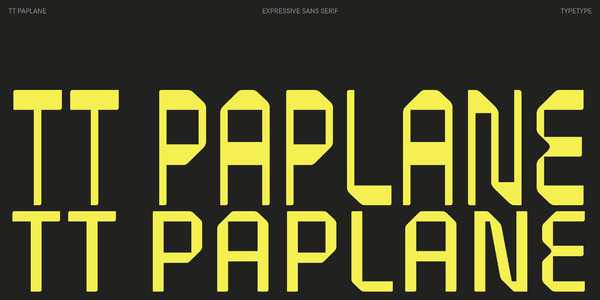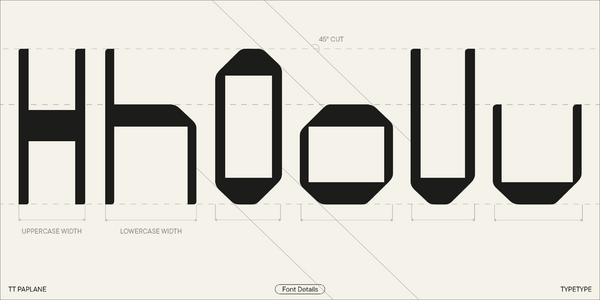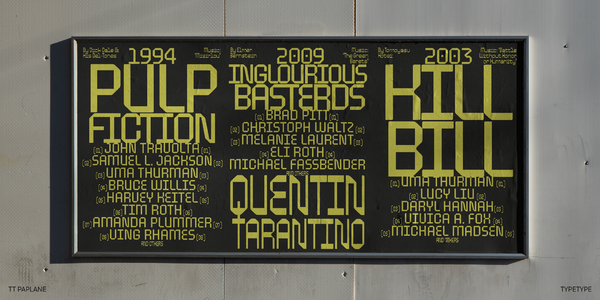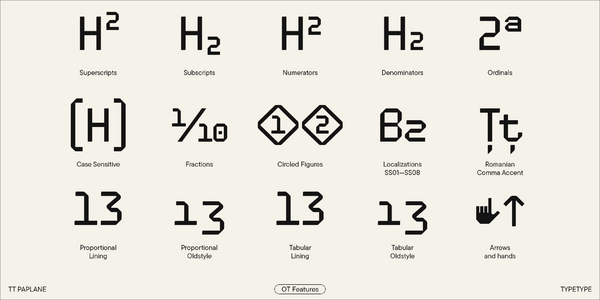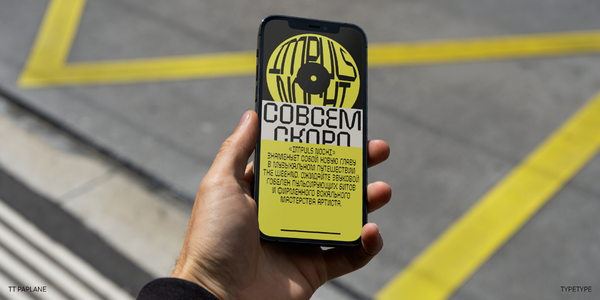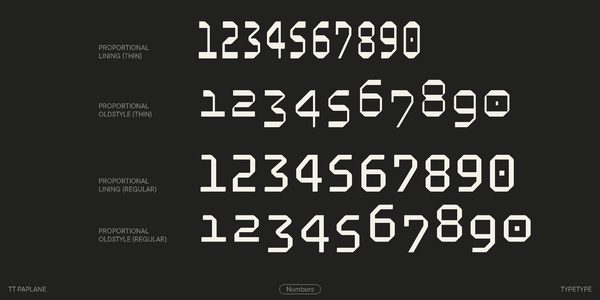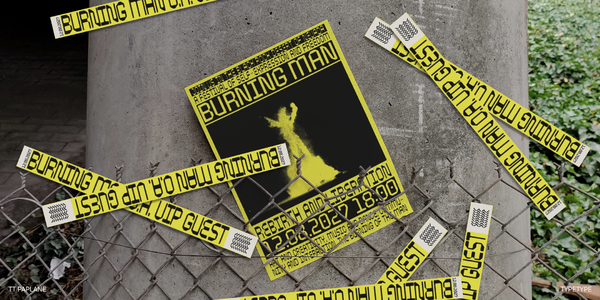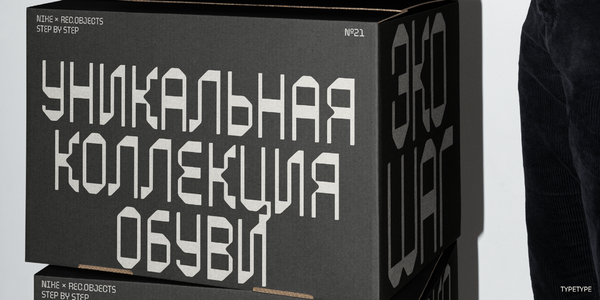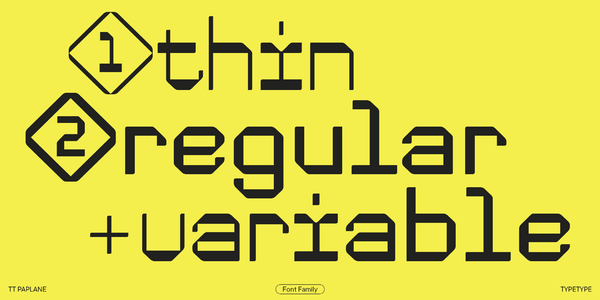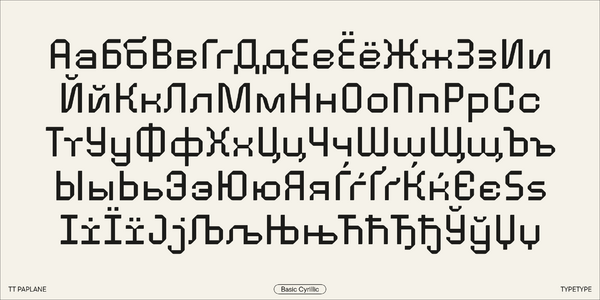
TT Paplane
TT Paplane — ТТ Паплэйн
Произносится «ТТ Паплэйн». «Paplane» — производное слово от paper (с английского «бумага») и plane (с английского «самолёт»). Буквы «TT» являются аббревиатурой названия компании.
TT Paplane — акцидентный сквадраченный гротеск с ностальгическим настроением. Логика букв этого шрифта выстроена так, будто они сложены из бумажной ленты.
TT Paplane — акцидентный гротеск, «прилетевший» из детства
На создание этого шрифта нас вдохновили воспоминания о детстве. Помните, как вы складывали самолетики из бумаги? Мы в свою очередь сложили из образа бумажного самолета целый шрифт. При всей визуальной модульности и «машинности» этот шрифт совершенно рукотворный и ассиметричный, а значит — живой и игривый. Второе начертание имеет сильный обратный контраст, который по своей логике и природе различается в прописных и строчных знаках. Такая особенность делает данное начертание уникальным и узнаваемым. Большая разница между двумя начертаниями значительно увеличивает возможности шрифтовой гарнитуры.
О гарнитуре TT Paplane
Встречайте новый акцидентный шрифт от TypeType — беззаботный TT Paplane, «прилетевший» к нам прямиком из детства!
TT Paplane — акцидентный сквадраченный гротеск. Название Paplane образовано от словосочетания «paper plane» («бумажный самолетик»). В нём отразилась идея нашего шрифта: логика букв выстроена так, будто они сложены из бумажной ленты.
Так, характерные черты этого гротеска — сквадраченные формы, 45-градусные срезы и обтекаемые внешние контуры, ассиметричные сглаживания вершин штрихов. Игривости шрифту придают разные пропорции строчных и прописных знаков. Среди цепляющих деталей — капли в кириллице, формы буквы «i» и кириллической «т», хвостики «ц» и «щ», засечки у букв «i» и «l».
TT Paplane включает два начертания с разной эстетикой: Regular и Thin. В регулярном начертании шрифт малоконтрастный и выглядит именно «бумажным». В Thin же появляется сильный обратный контраст при тех же формах глифов, из-за чего при наборе рисунок шрифта начинает быть похожим на штрихкод. Прописные символы в обоих начертаниях заметно уже строчных, а сами пропорции букв стремятся к моноширинным. Кроме того, в гарнитуру входит вариативный шрифт, меняющийся по толщине.
Этот необычный шрифт будет здорово смотреться в дизайне плакатов и афиш, в оформлении упаковки и брендинге, как яркий акцент на сайтах или в приложениях. С его помощью вы можете придать своему дизайну неформальное настроение, стилизовать его под атмосферу 80-х или 90-х годов, добавить проекту самобытности и выйти за привычные рамки.
TT Paplane включает:
• 3 начертания: 2 прямых и 1 вариативный шрифт;
• 757 знаков в каждом начертании;
• 24 OpenType фичи;
• Поддержка более 230 языков.
Отправьте вашу фантазию в свободный полёт с TT Paplane!
Марина Ходак
Антонина Самохина
Юрий Наконечный
Елизавета Островская
ss01 | Circled Figures
ss06 | Bashkir localization
ss08 | Bulgarian localization
dlig | Discretionary Ligatures
onum | Oldstyle Figures
ss09 | Serbian localization